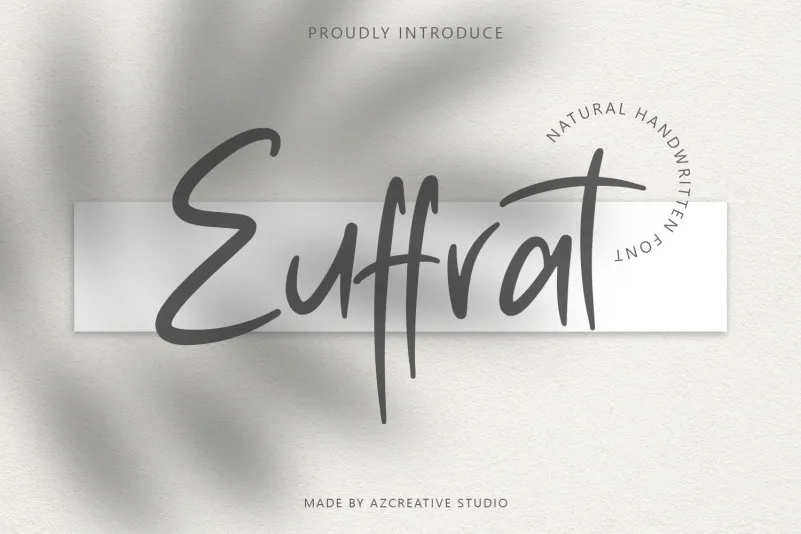
Euffrat Font – Fonte Grátis
Euffrat Font
Esta fonte está projetada para oferecer uma sensação relaxante e amigável ao usuário. É perfeitamente adaptada para se tornar parte de layouts pessoais ou designs simples, onde você deseja transmitir uma atmosfera descontraída e acolhedora. Desenvolvida por azcreativestd, essa fonte está PUA encoded, o que significa que você pode acessar todas as gílias e borrões com facilidade. Se estiver procurando uma fonte escrita a mão para seus projetos digitais de design, “Euffrat Font” é uma excelente escolha. Sua natureza relaxada e acolhedora torna-a ideal para aplicativos variados, desde cartazes pessoais até designs de redes sociais que buscam transmitir um sentimento casual e bem-humorado.